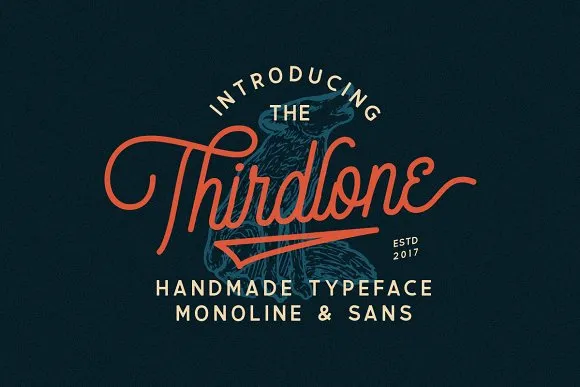
Thirdlone Font Duo – Download Grátis
A Thirdlone Font Duo é uma incrível combinação de tipo script e sans-serif que cria designs elegantes, modernos, vintage e retro ao mesmo tempo. Desenvolvida pelo designer Letterhend, essa fonte traz um rico acervo de ilustrações em vetor para personalizar suas criações ainda mais. Os temas incluem aventura, natureza, animais, praia, mar, festas, entre outros. Com milhares de objetos variados disponíveis, você pode criá-lo conforme seu gosto e necessidade. Essa fonte é perfeita tanto para design têxtil quanto para logomarca, assinatura, headlines e letras decorativas ou frases. Ela está disponível em maiúsculas, minúsculas, pontuação, símbolos e numerais, além de set alternativo, ligaturas e suporte a múltiplas línguas. Com Thirdlone Font Duo, você terá tudo o que precisa para personalizar suas criações de forma única e sofisticada, sem deixar nada à desejar ao seu design.